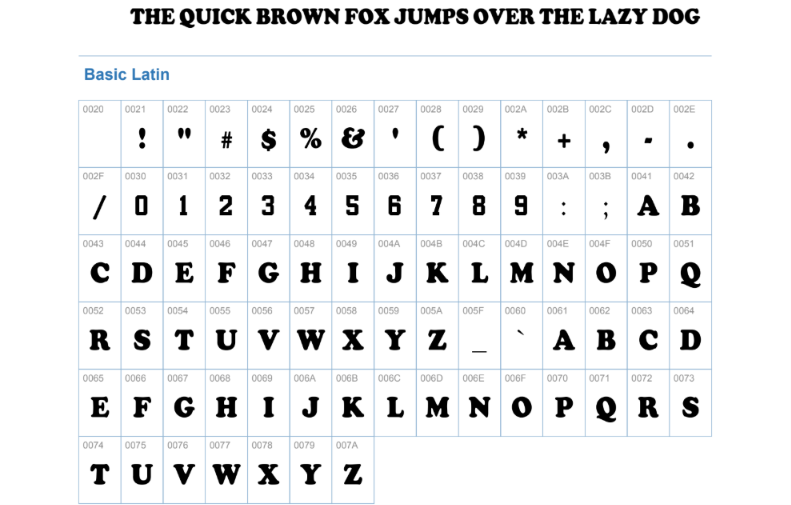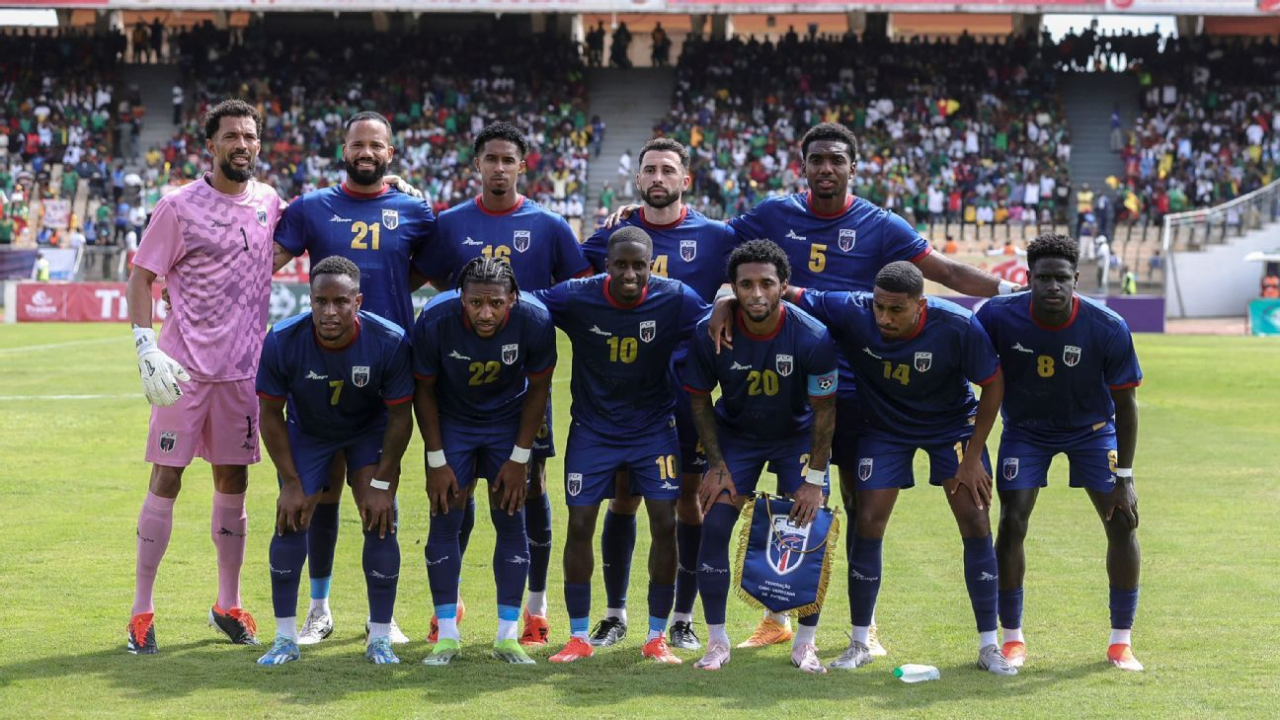
A estreia de Cabo Verde na Copa do Mundo 2026 é histórica, e cada detalhe visual carrega o peso dessa conquista. A identidade dos Blue Sharks vai muito além do uniforme: a tipografia oficial da temporada traduz em traços a força, a união e a cultura arquipelágica do país. Desenvolvida em parceria com a Capelli Sport, a fonte é um símbolo de orgulho para torcedores e um prato cheio para designers que buscam referências autênticas no universo esportivo.
Com formas geométricas inspiradas nas rotas aéreas que conectam as ilhas de Cabo Verde, a tipografia carrega um simbolismo único. É a identidade da nação impressa em cada número e nome, unindo modernidade e tradição em um só traço.
Detalhes técnicos da fonte
Aplicação no uniforme
- Home (titular): números em branco sobre o azul-marinho, garantindo alto contraste.
- Away (reserva): numeração em azul ou vermelho sobre o fundo branco.
O número confere, porém as letras não